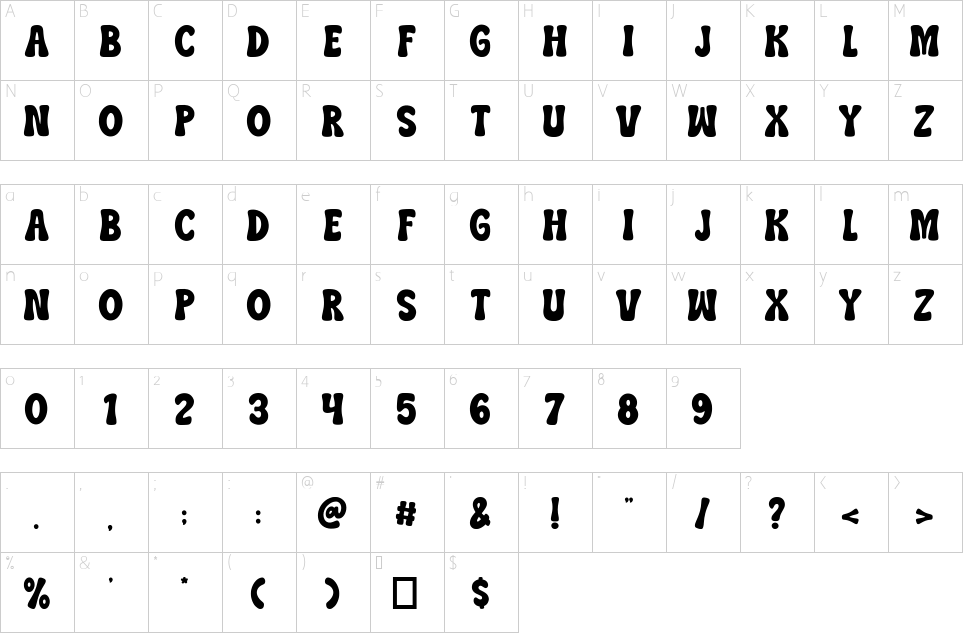
A fonte Groovy Style é uma ótima escolha para quem procura algo descolado e vibrante para decorar seus projetos digitais. Desenhada pelo designer não informado, a Groovy Style apresenta um estilo fresco e animado que se destaca com suas linhas curvas levemente dobradas e tons de cores vibrantes. Ela foi especialmente planejada para dar vida à sua identidade visual ou adicionar um toque divertido aos designs. A fonte já foi baixada 224 vezes, o que mostra seu potencial popular e a qualidade da sua designação. Perfect para criar uma atmosfera única em sites, aplicativos, logotipos e muito mais. Descubra o poder de Grungy Style – Fontes Free, você vai adorar!